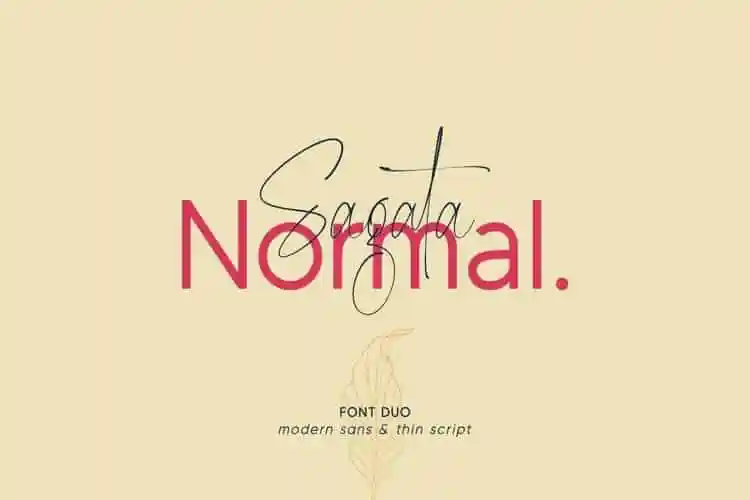
Sagata Normal Font Duo – Download Grátis
A Sagata Normal Font Duo é uma paleta de duas fontes que traz modernidade e elegância de maneira envolvente. Inspirada nas combinações entre caracteres círculo-de-texto e sans-serif, esta fonte oferece um equilíbrio harmonioso e profissional. As linhas retas do Sans Serif contrastam suavemente com as curvas mais fluidas do Script, criando uma composição que é tanto funcional quanto estética. Com a Sagata Normal Font Duo, você pode manter seu design consistente ao mesmo tempo em que adiciona um toque sofisticado aos seus projetos de texto. Esta combinação moderna e versátil se adapta a diversas necessidades gráficas, desde rótulos informativos até headlines assertivas. Trazendo uma dose extra de personalidade sem comprometer o fluxo leitura, ela é uma escolha perfeita para os criativos que buscam um estilo único em sua obra.